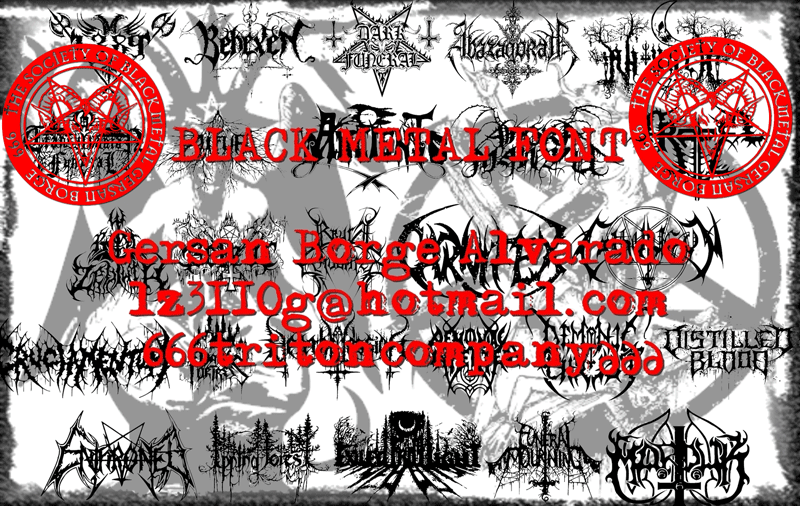
Font name: | Black Metal G |
Categories | Dingbats, Logos |
Author: | Gersan Borge A |
Note by Gersan Borge A | |
es una buena fuente las mejores bandas de black metal y de diferentes partes del mundo.. |